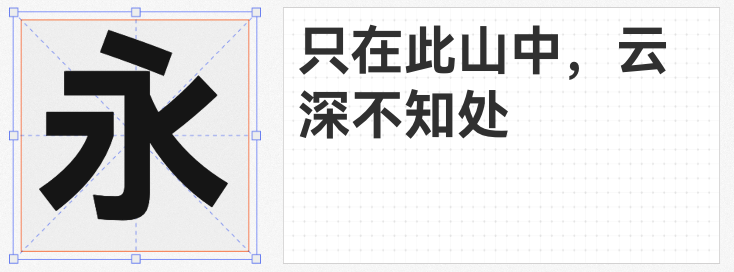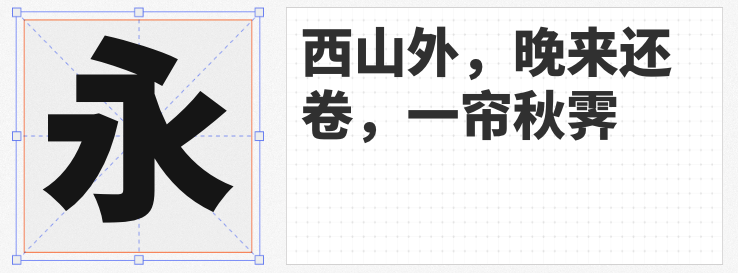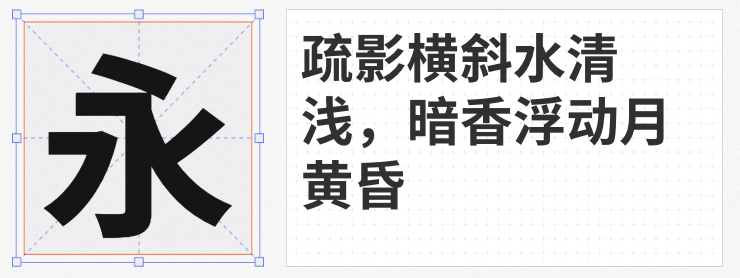
在平面设计与数字媒体创作中,黑体因其简洁现代、易读性强的特性,成为品牌标识、标题排版、UI设计的首选字体类型。本文精选四款开源免费商用黑体字体,涵盖多语言支持、独特字形改造与人文美学设计,助力设计师突破创意边界。
由Adobe与Google联合开发的思源黑体,是开源字体领域的里程碑之作。其初始版本提供七种字重(ExtraLight至Heavy),2.2版本新增可变字重功能,支持通过软件无级调节笔画粗细,满足从正文到标题的全场景需求。字体覆盖简体中文、繁体中文、日文、韩文及拉丁字母系统,总字符数超65万,兼容性极强。思源黑体 SC Bold以均衡的笔画粗细与现代感设计,成为多语言排版、国际化品牌设计的理想选择。
华为定制的HarmonyOS Sans SC Bold,在功能性基础上融入书法美学。短笔画采用横平竖直的简约设计,长笔画(如撇、捺、弯钩)则融入传统书法的笔势韵律,形成视觉张力。字体重心居中,中宫适度开放,确保小字号下的清晰度与大字号下的稳重感。其多语言支持覆盖全球105种语言,并支持字重与中宫双重无级调节,适用于智能终端界面、动态海报等需要灵活适配的场景。
基于未来荧黑改造的江城正君体,通过横向减细、纵向增粗的独特处理,形成兼具黑体稳重与宋体雅致的混合风格。设计师针对数字“4”“7”及字母“K”“k”进行优化,消除原字体不美观的笔画形态。该字体提供400W、500W、600W三种字重,支持GB 18030标准全字符集,适用于文化创意海报、复古风格包装设计等领域,为作品增添个性化辨识度。
句读黑体以思源黑体为基底,融合更纱黑体、FiraGO等字体的多语言优势,支持简体中文、繁体中文、日文、韩文、藏文、阿拉伯文等50余种文字系统,总字符数达4.7万。字体采用等宽数字与开放字怀设计,确保多语言混排时的视觉统一性。其Hans Heavy字重以粗壮笔画强化标题冲击力,同时保持笔画转角的柔和处理,适用于跨境电商平台、国际会议物料等需要跨文化传播的场景。